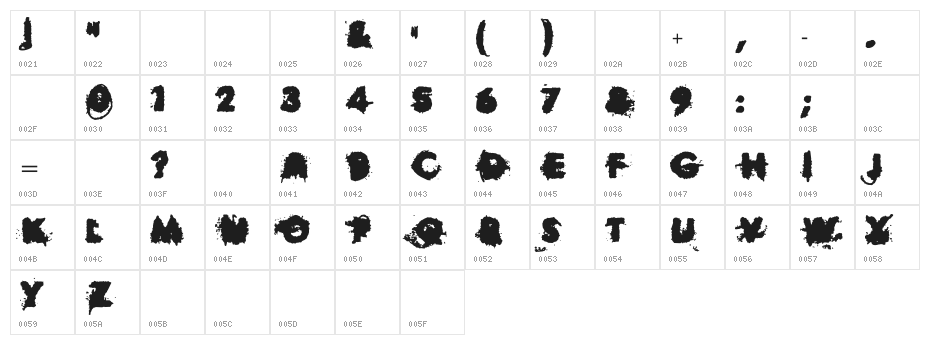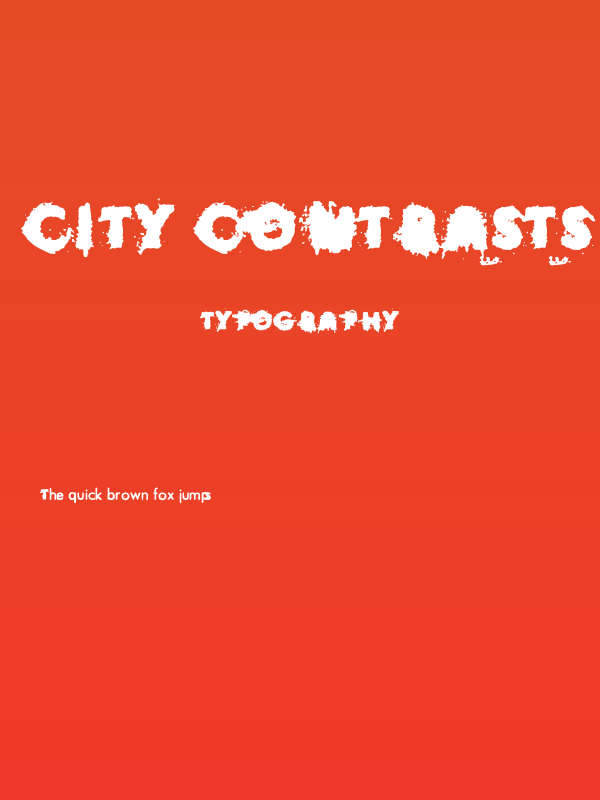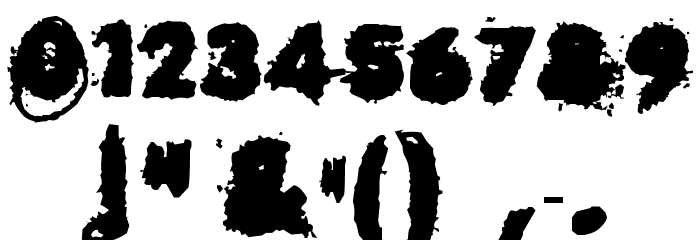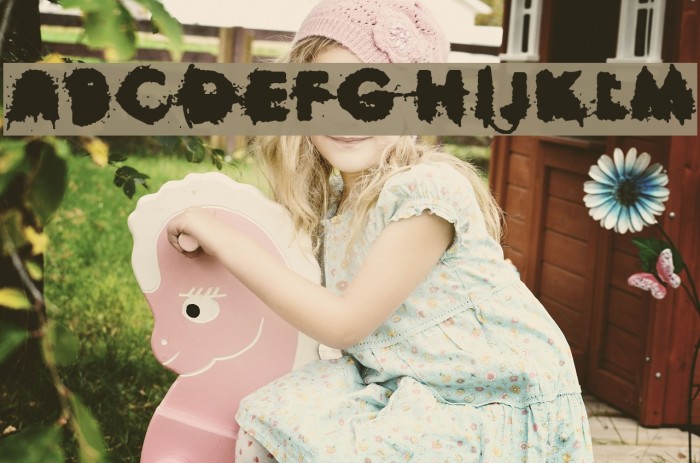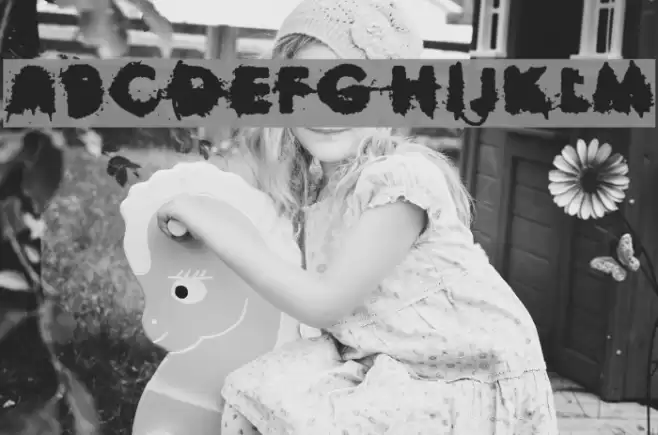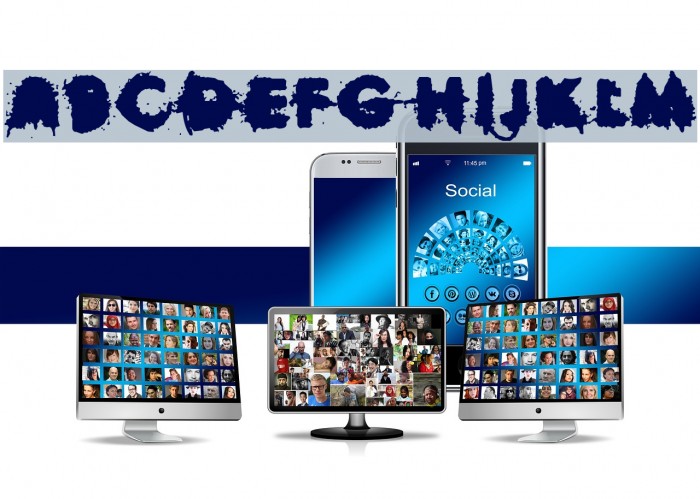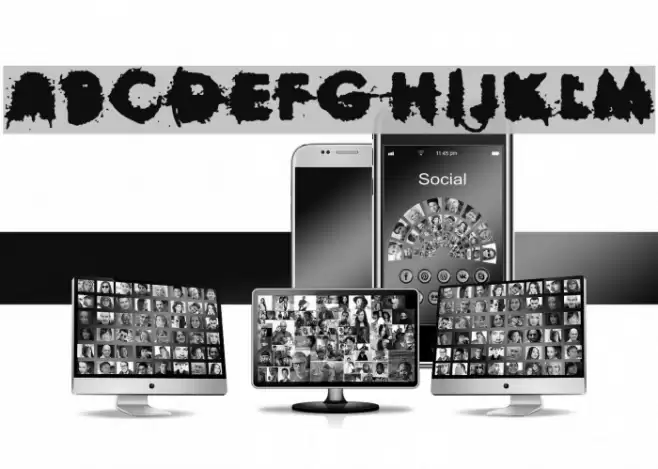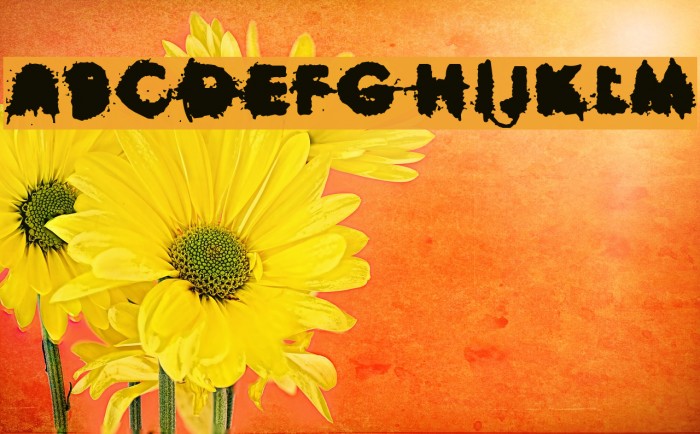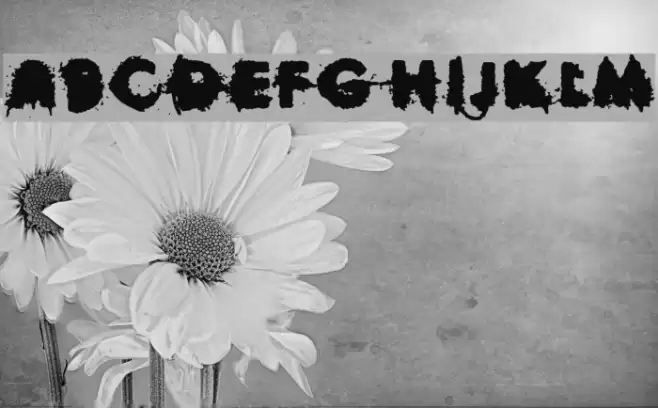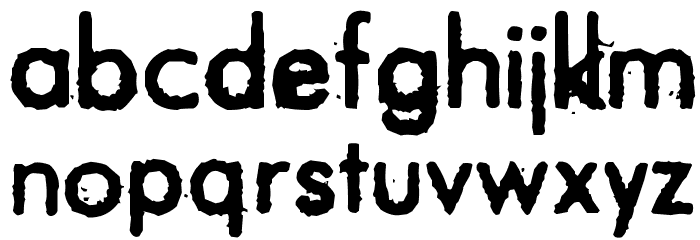
City Contrasts Font
✎ Distorted Eroded
| Categorii | Distorted Eroded |
| Stil general | Urban, Grunge |
| Caz de utilizare | Headlines, Posters, Branding |
| Proiecte propuse | Ideal for street art-inspired designs, album covers, posters, and branding that seeks an edgy, rebellious look. |